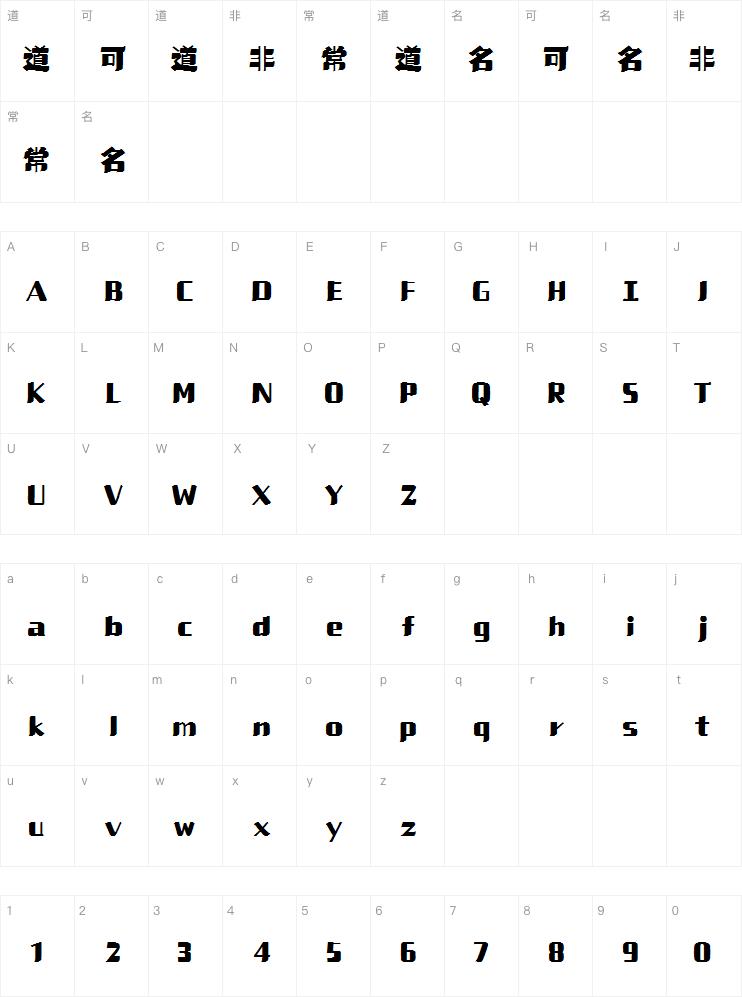
山海雅致黑,是一款全新的字体,包含汉字9169个,符号200+个。该字体是一款综艺标题黑体字体,是一款具有强劲视觉冲击力的综艺风格标题字体。字形充实填满整个字框,造型硬朗,直线的笔画构成坚实有力,简洁明了的笔画切角;字形比例按照宽高10:9的比例设计,使得字体厚重宽博;同时笔画带有尖角装饰,使得字形带有律动感,带来强有力的视觉冲击效果;粗细笔画交错,在律动般的粗细笔画交错中寻求平衡,使得字体有着韵律感。该字体在综艺体的基础上做了诸多创新,使得该字体既有着流动的美感,又有着端肃的凝重,在正式用字场合落落大方,在日常使用环境中不失亲切友好,能够在保留综艺体基本特征的基础上更能适应当下时尚潮流的需要,助力各大新产品夺取标题主战场。